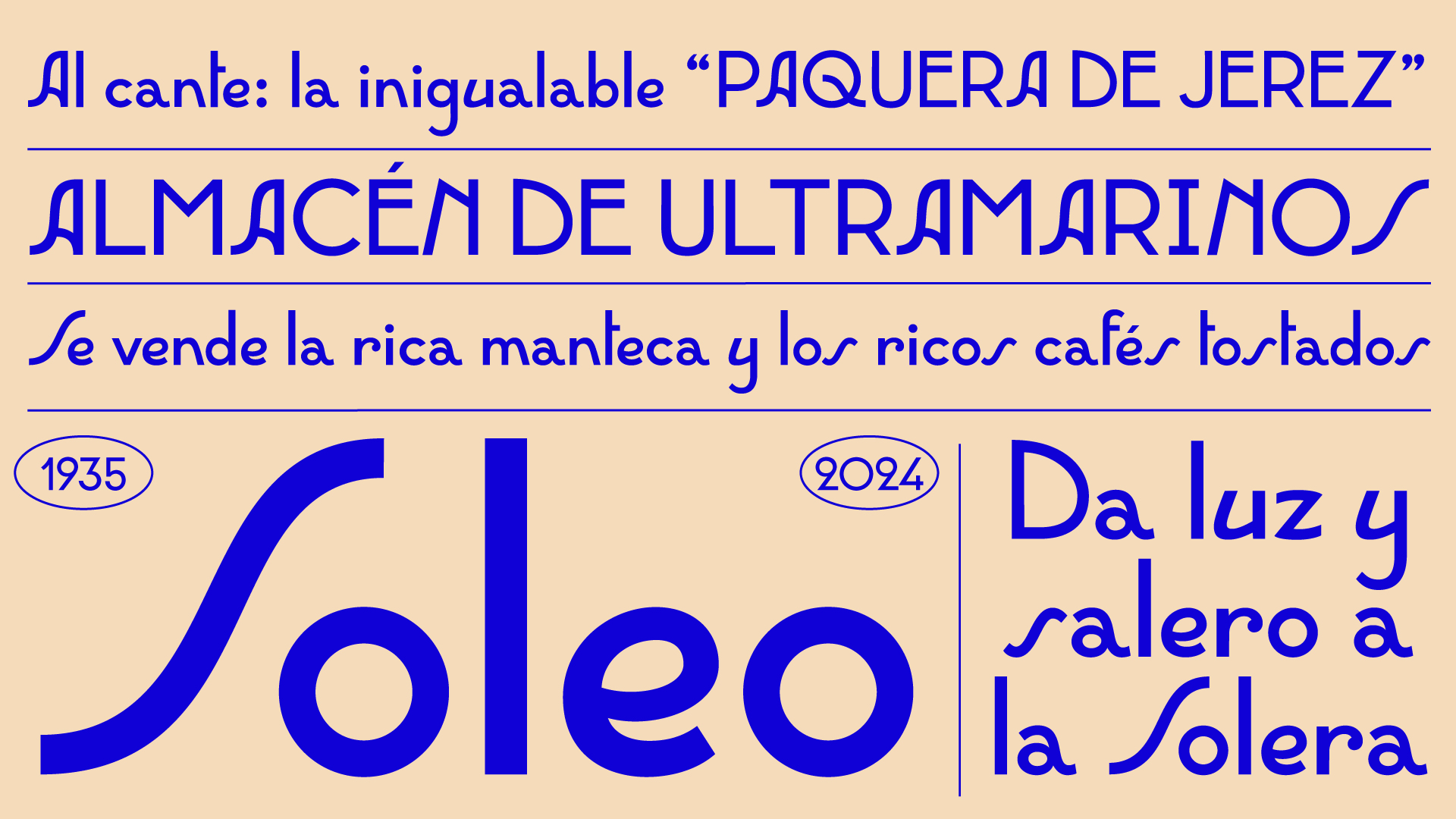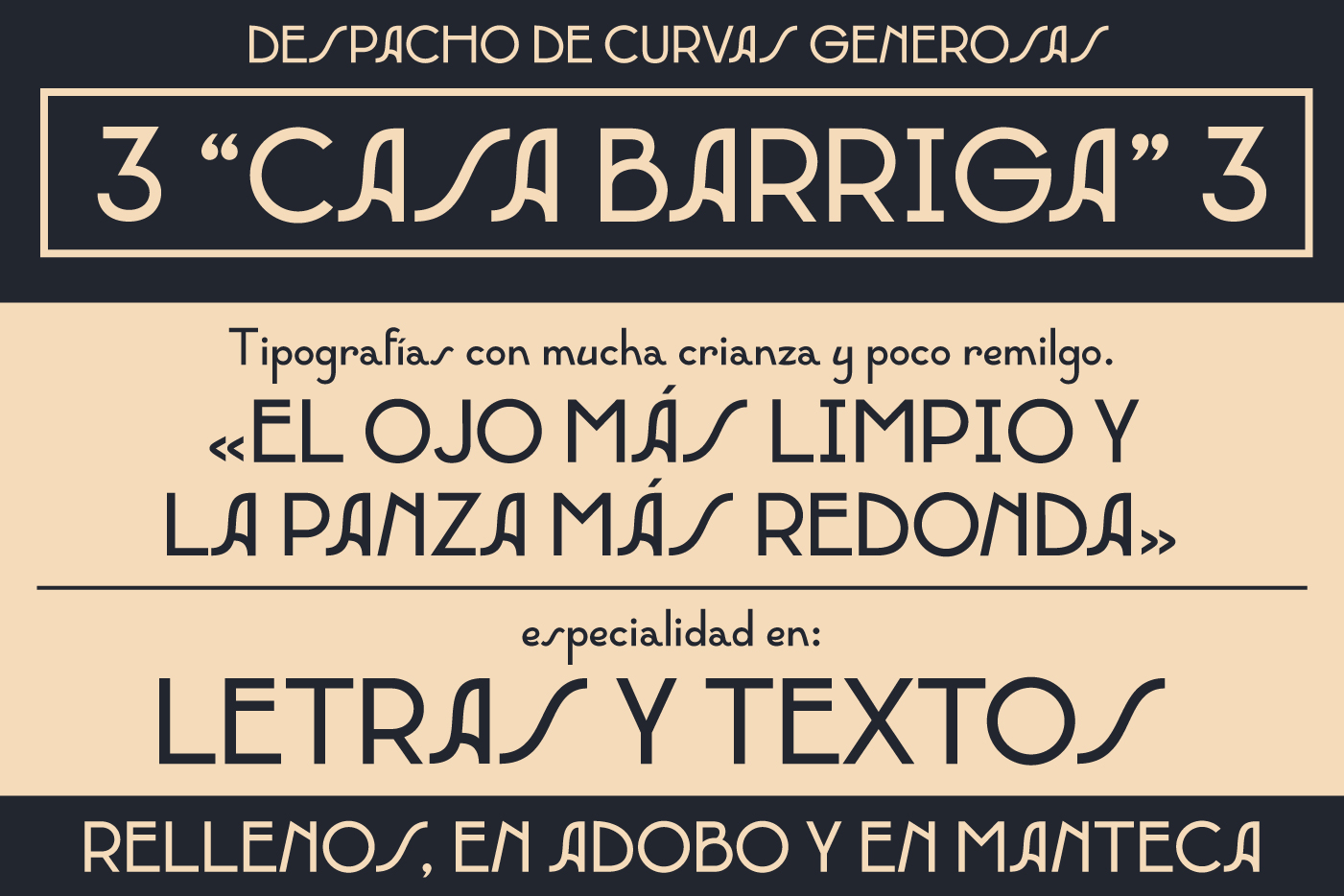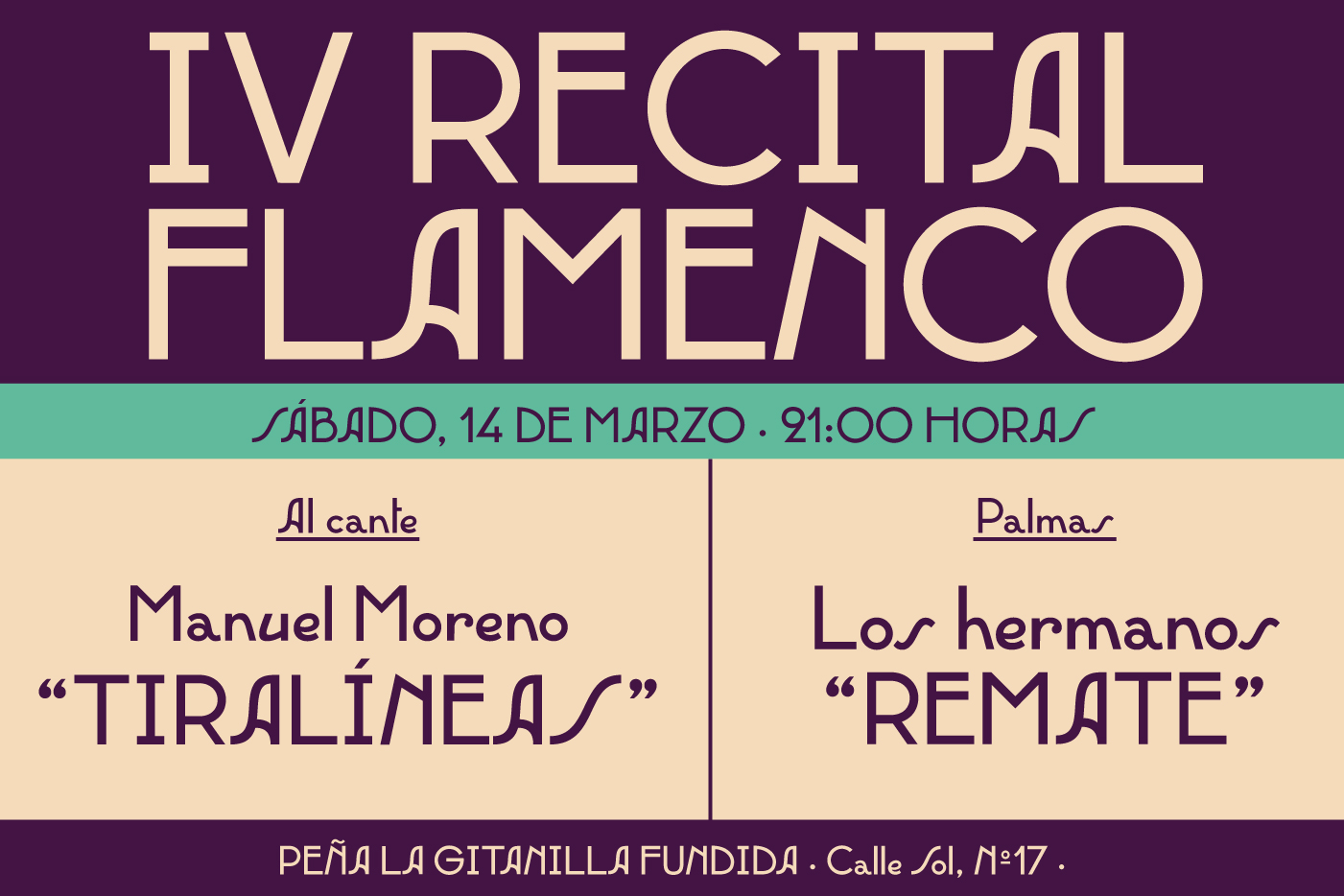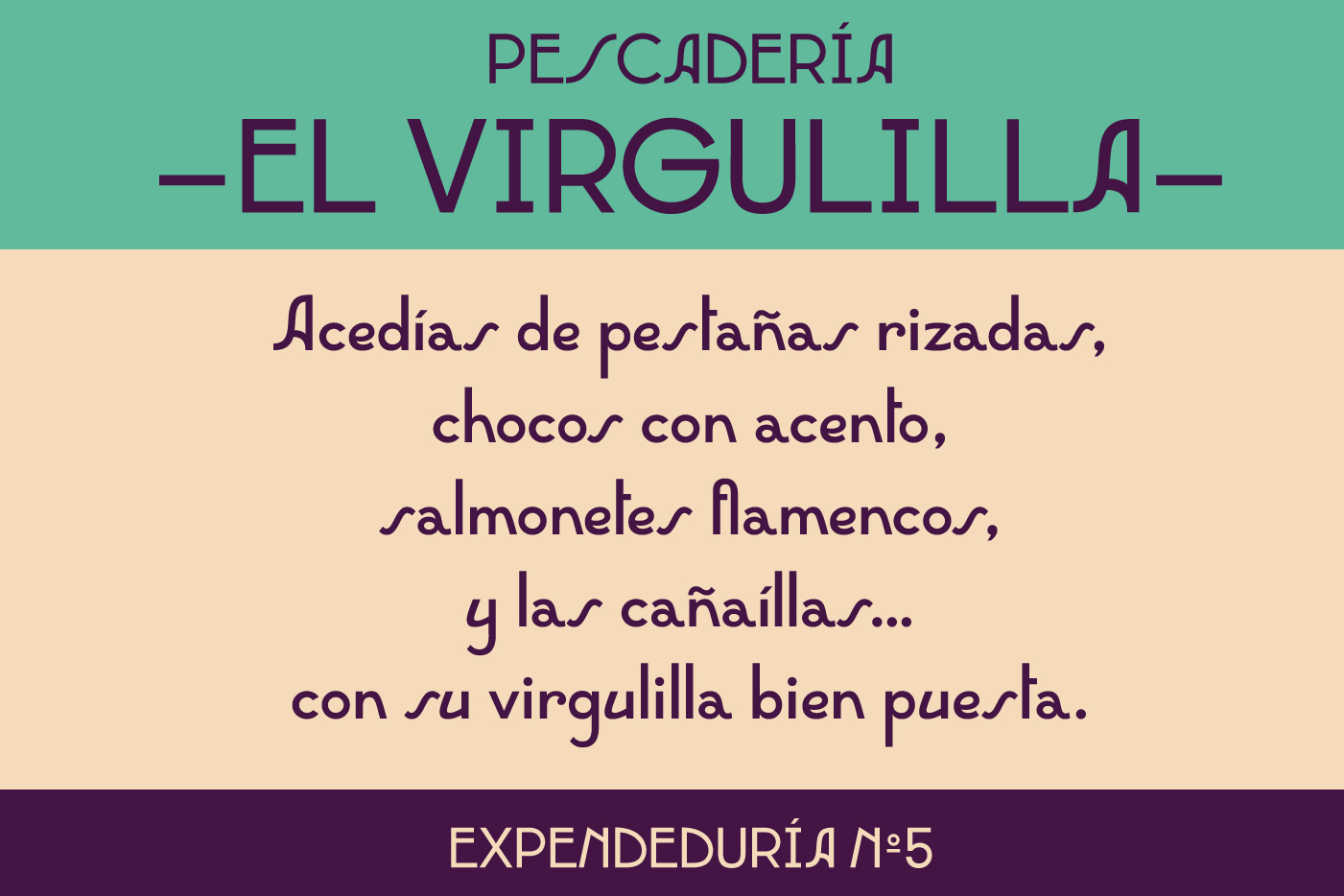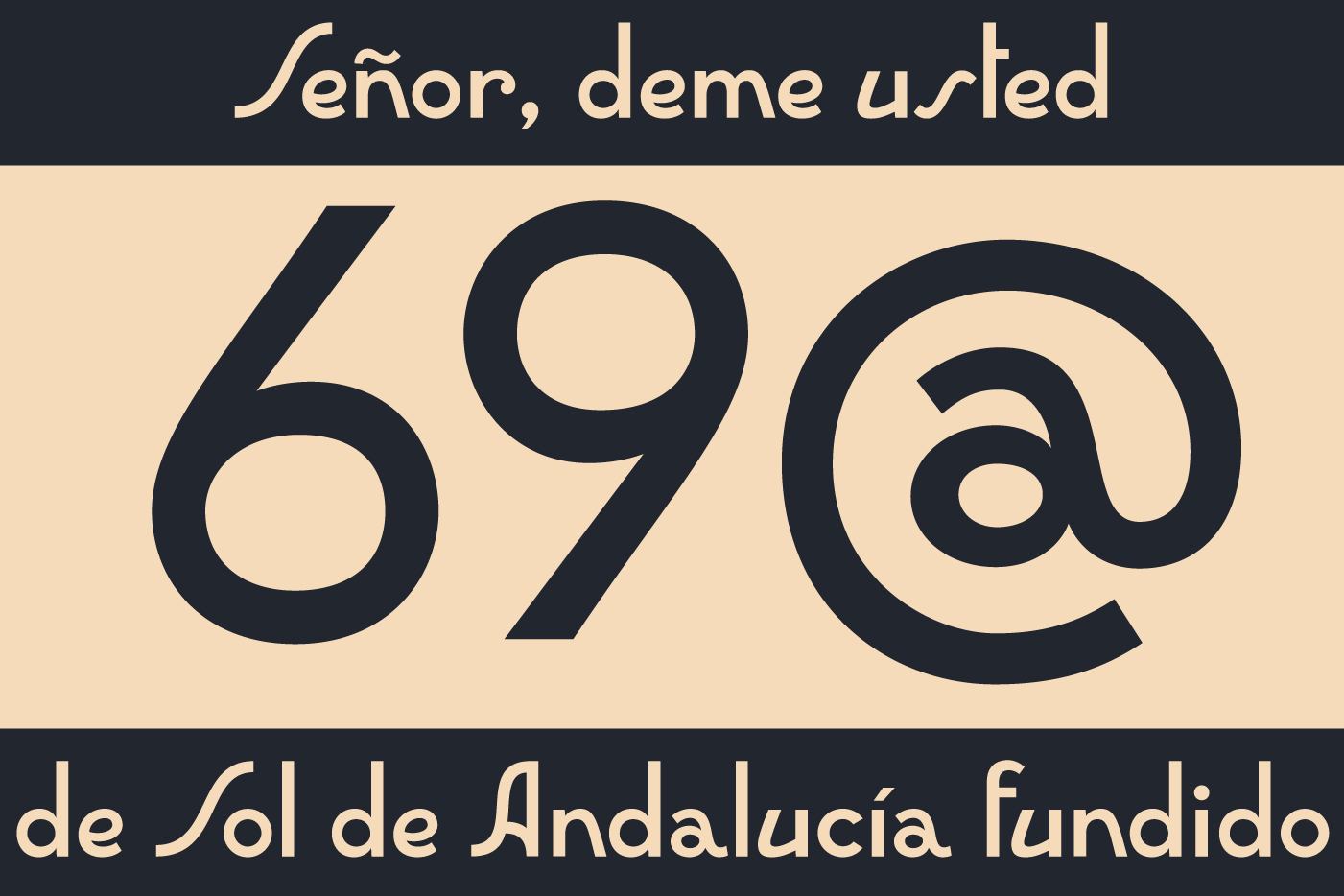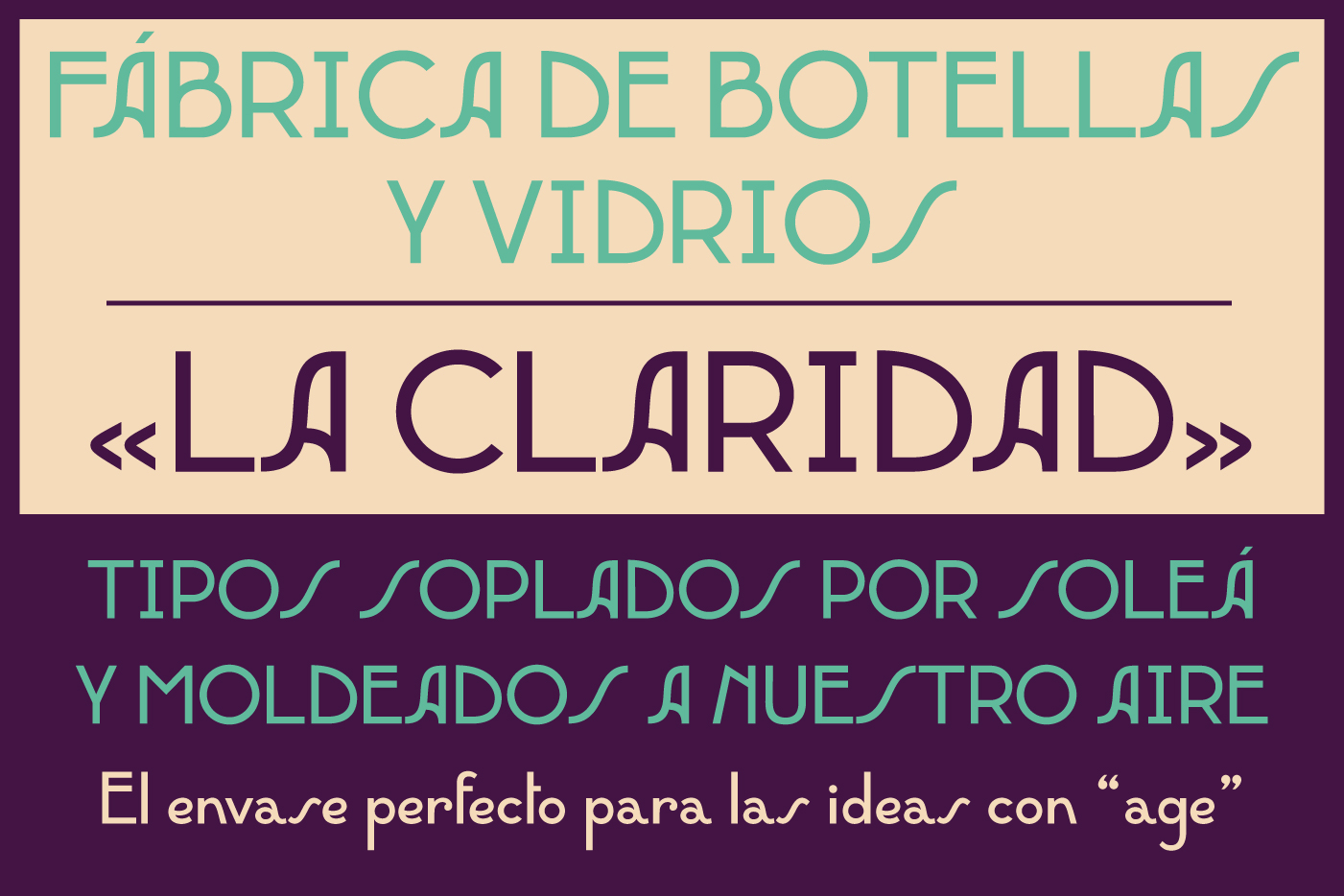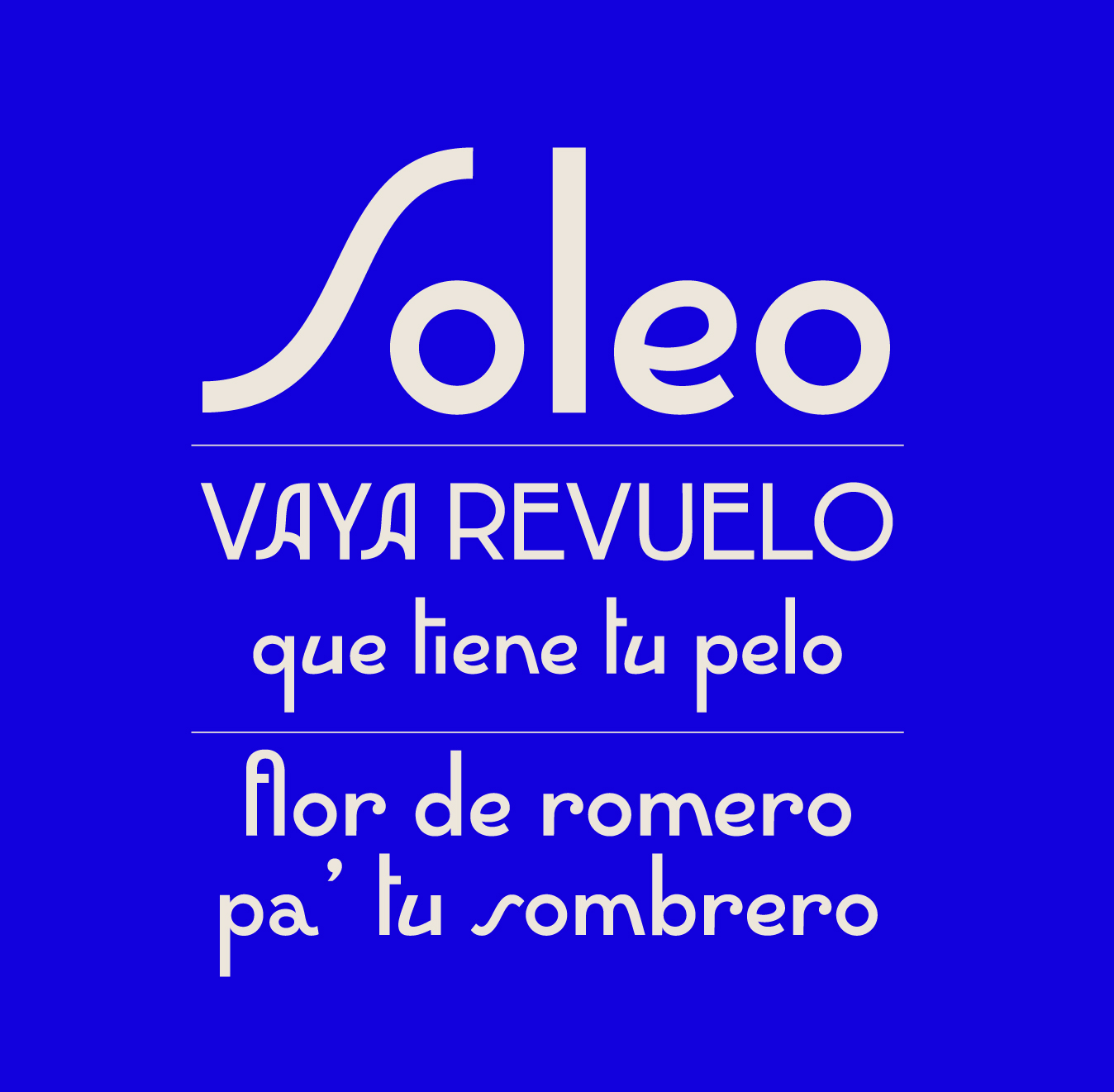
Soleo
Careleria castiza
Soleo
Cartelería castiza
Tio Pepe y Pérez solero
La pareja perfecta de Solera
Soleo es una tipografía de estilo Art Decó, pensada para dar luz y salero a su «hermana» Solera. Es el perfecto homenaje a Luis Pérez Solero, completando el maravilloso trabajo que hizo para la gráfica de la marca Tio Pepe. Además, hacemos homenaje a el proceso de soleo, tan característico del vino, ya que es una técnica que permitía ganar graduación a la uva, mediante su exposición al sol. Es «Sol de Andalucía embotellado».
Desde este Despacho de Tipos, no solo fundimos letras, sino que también nos interesa trabajar con aquella publicidad de la época. Somos conscientes de que estamos hablando de uno de los mayores iconos que se han desarrollado en nuestro país, y de que Jerez ha generado un imaginario inigualable. Desde esta fundición queremos seguir manteniendo el legado de aquellas maravillosas agencias de publicidad jerezanas.
Del cartel a la rotulación
Pérez Solero le dió una caligrafía tan característica a Tio Pepe, que destacaba en cualquier tipo de formatos. Estudiamos minuciosamente el archivo. Tanto el cartel original como las fotografías de aquellos años 30; donde se rotularon plazas, tranvías y autobuses. Vimos catálogos y publicidad en carretera, comparándolos con otros productos como «Soberano», o incluso, con la propia firma de Solero, viendo similitudes gráficas y elementos en común.
Ideal para grandes formatos
Soleo destaca porque rescata elementos gráficos que huelen a Jerez. Utilice Soleo en sus mejores proyectos de identidad, para rotular su negocio o para maquetar carteles como si usted fuese el propio Pérez Solero.
Soleo
Soleo es la acopañante ideal de su «hermana» Solera. Una tipografía Art Decó que da luz y salero a sus diseños. 433 glifos en formato .otf para entornos impresos y .woff para formatos digitales. Utilice Soleo en sus mejores proyectos de identidad, para rotular su negocio o para maquetar carteles como si usted fuese el propio Pérez Solero.